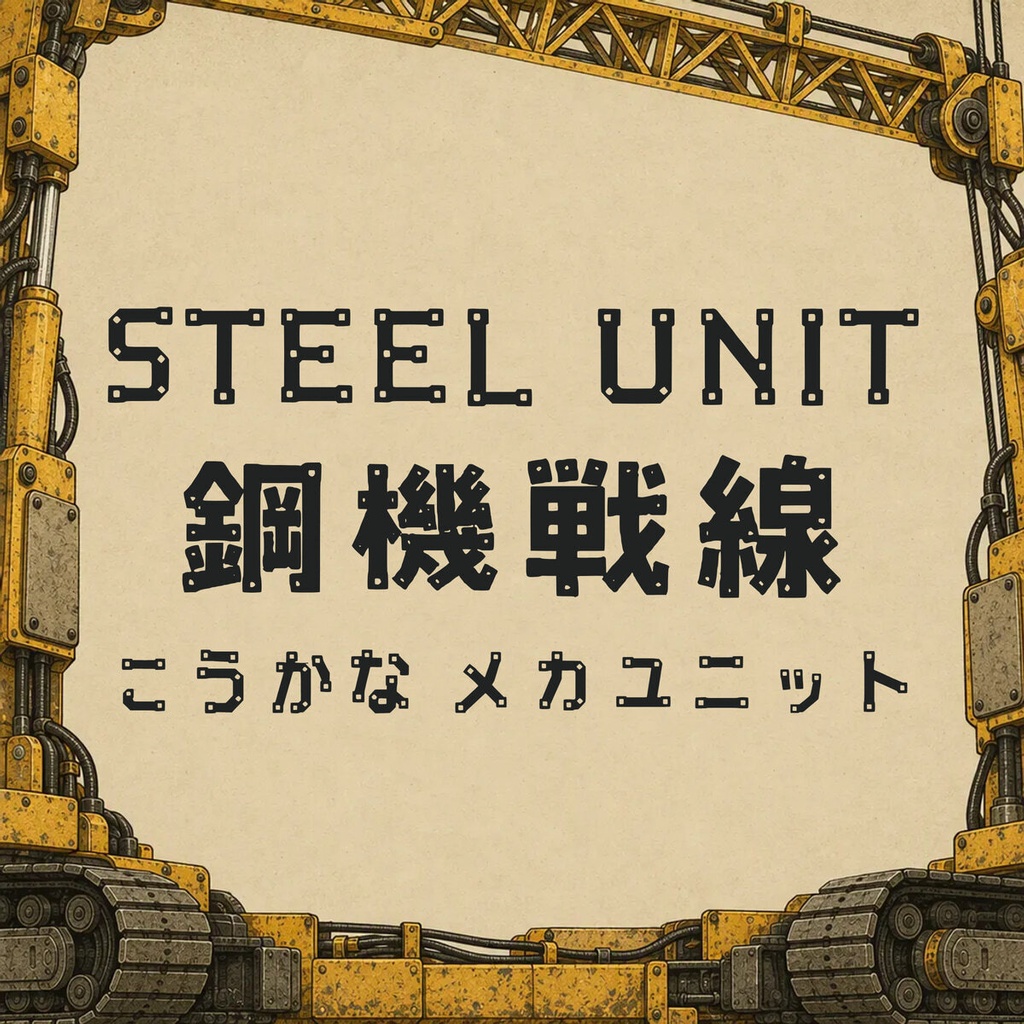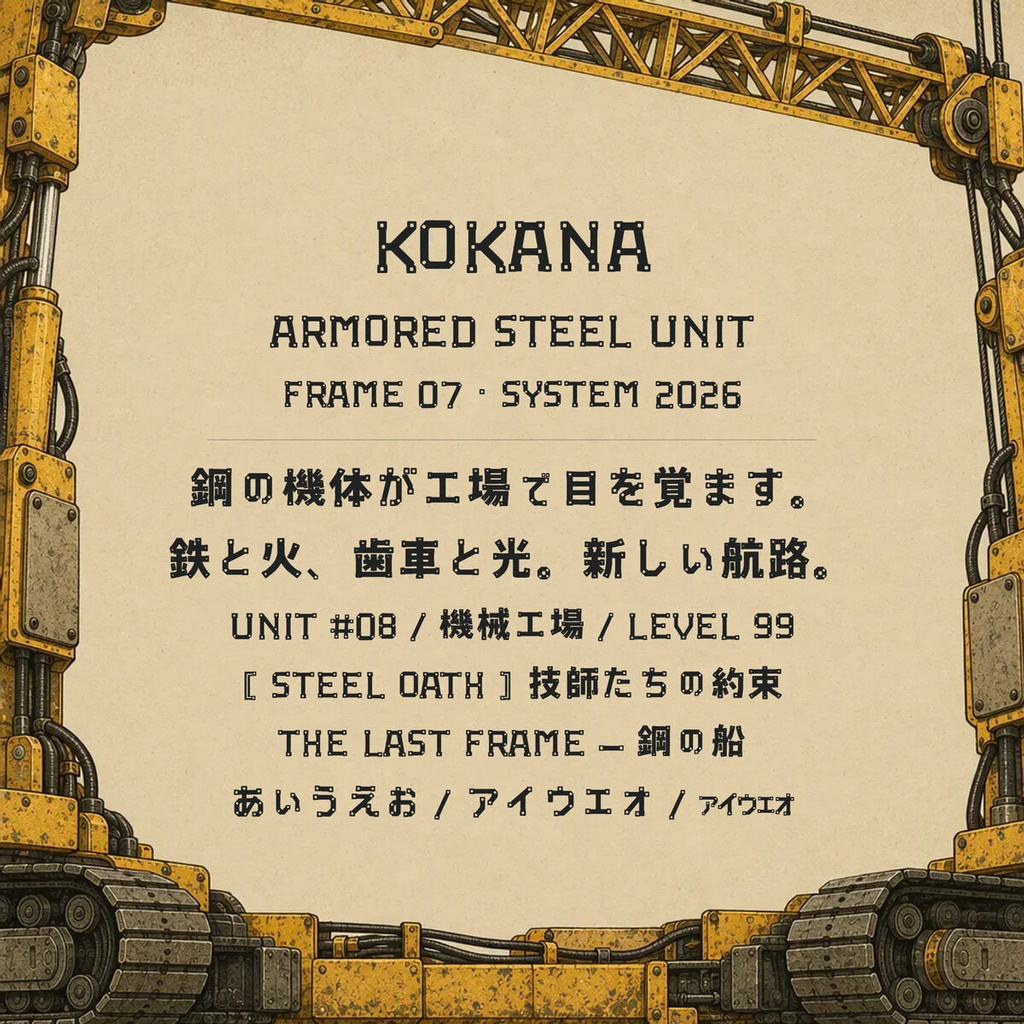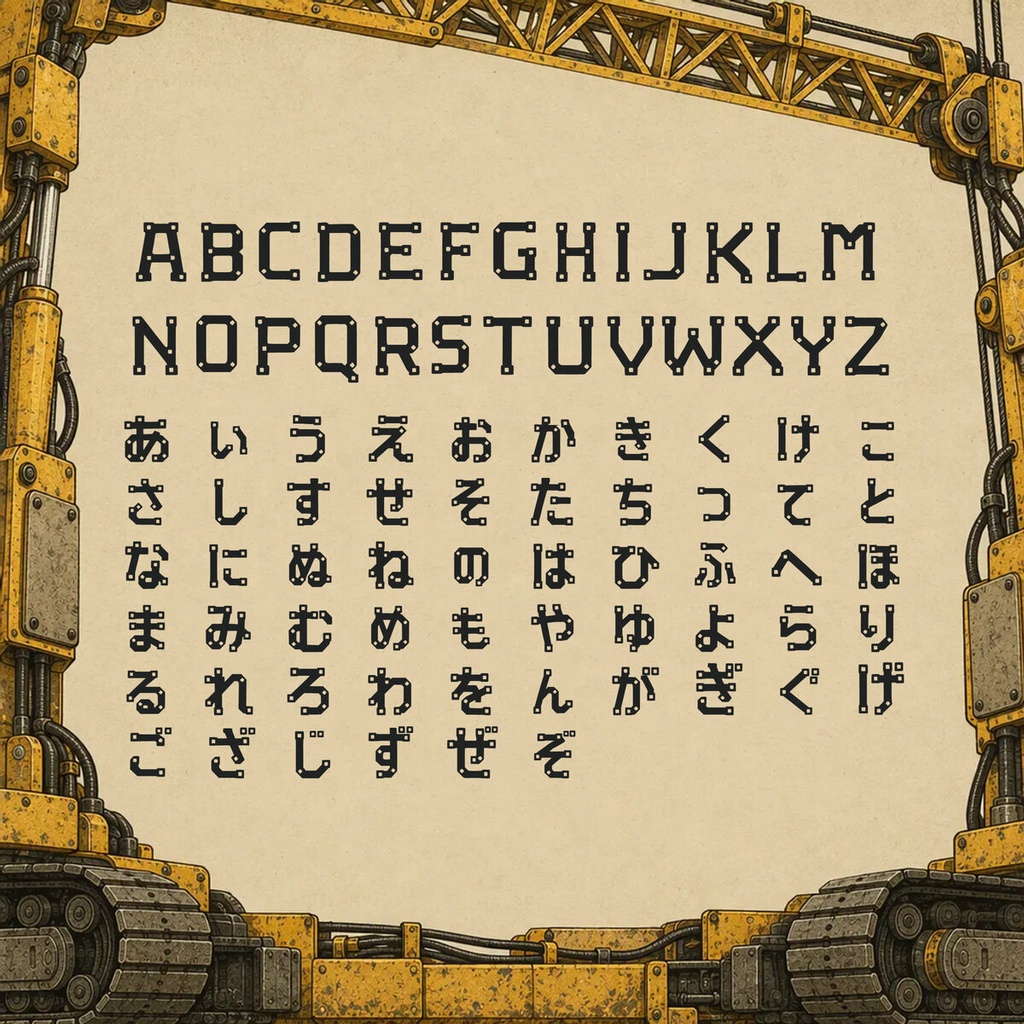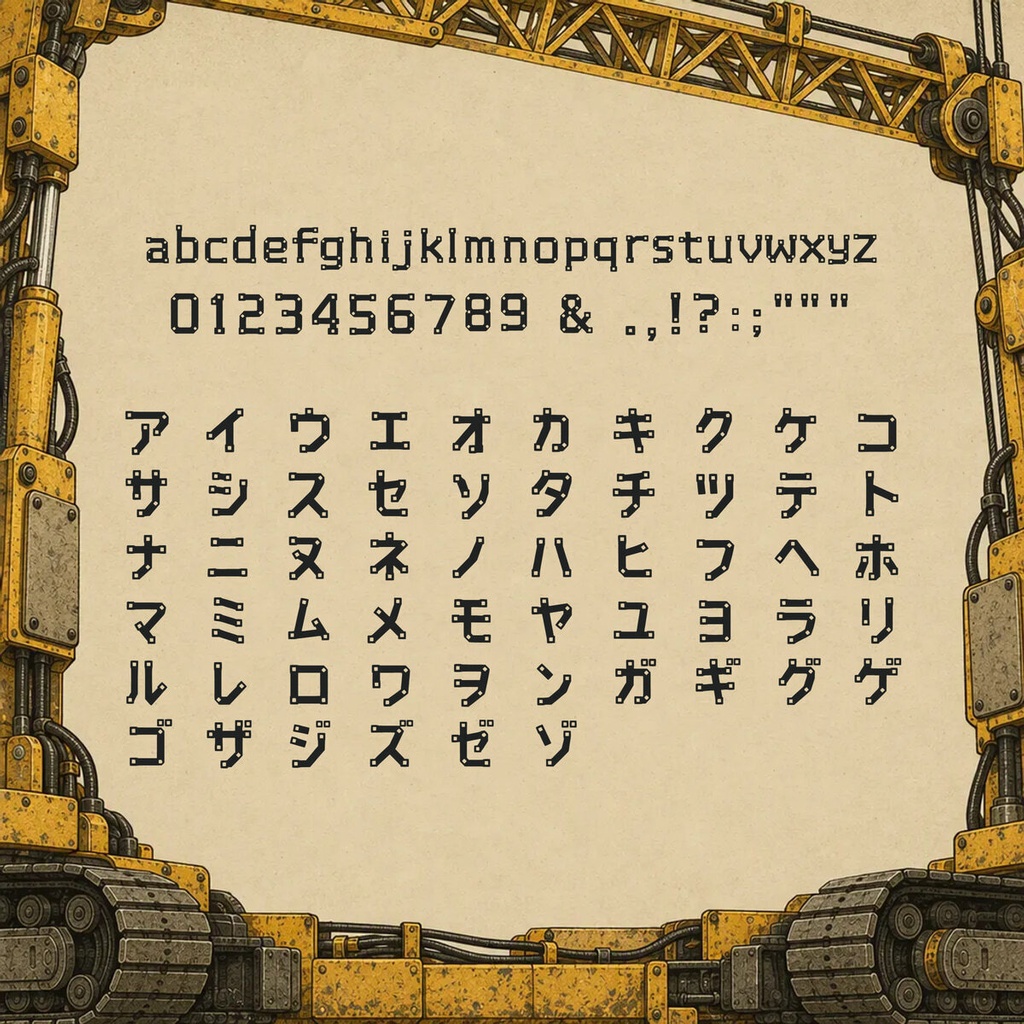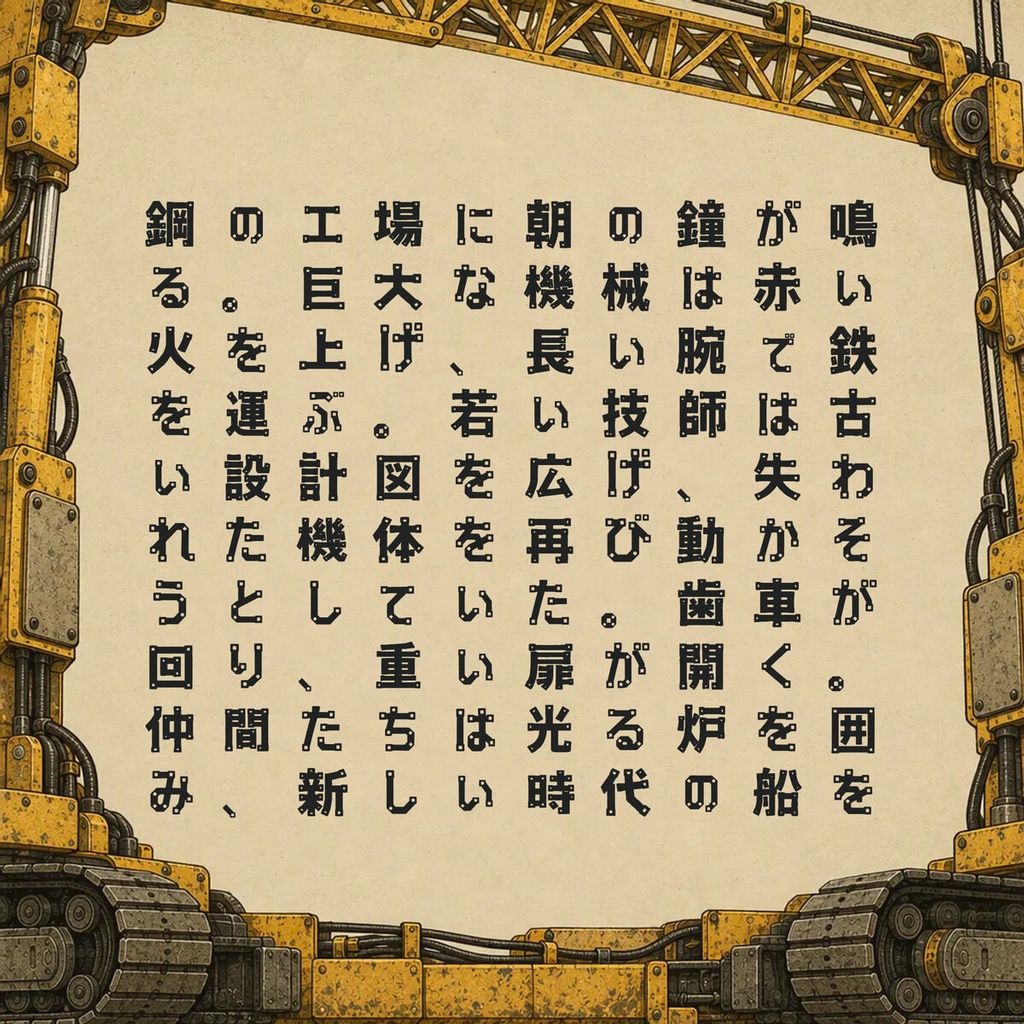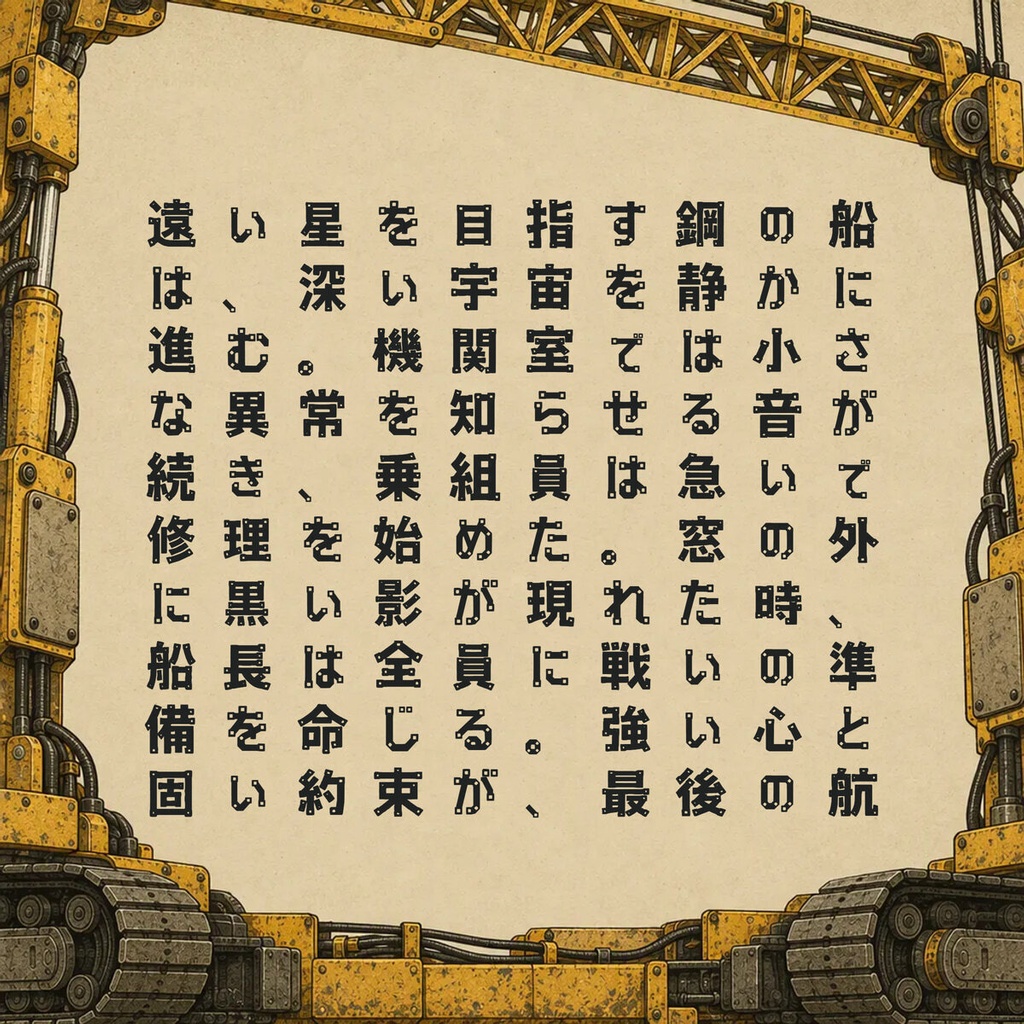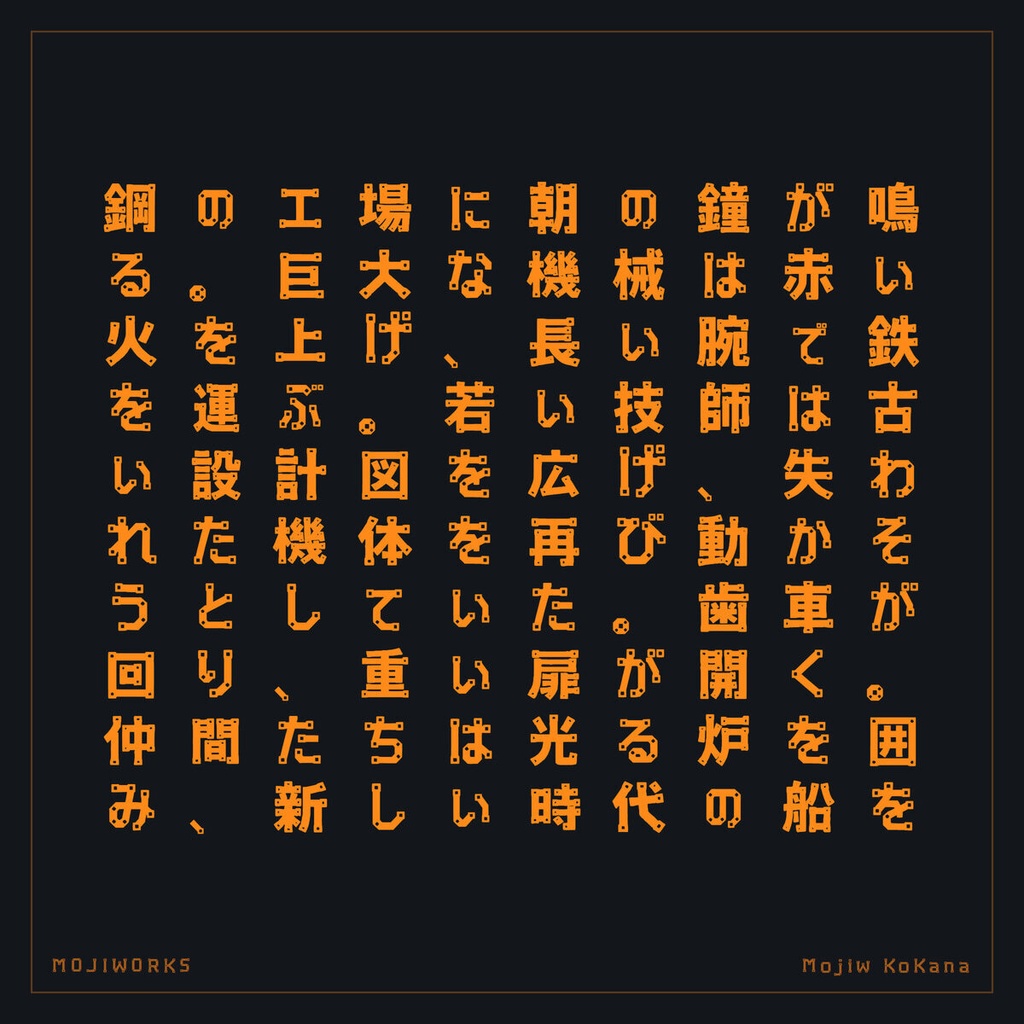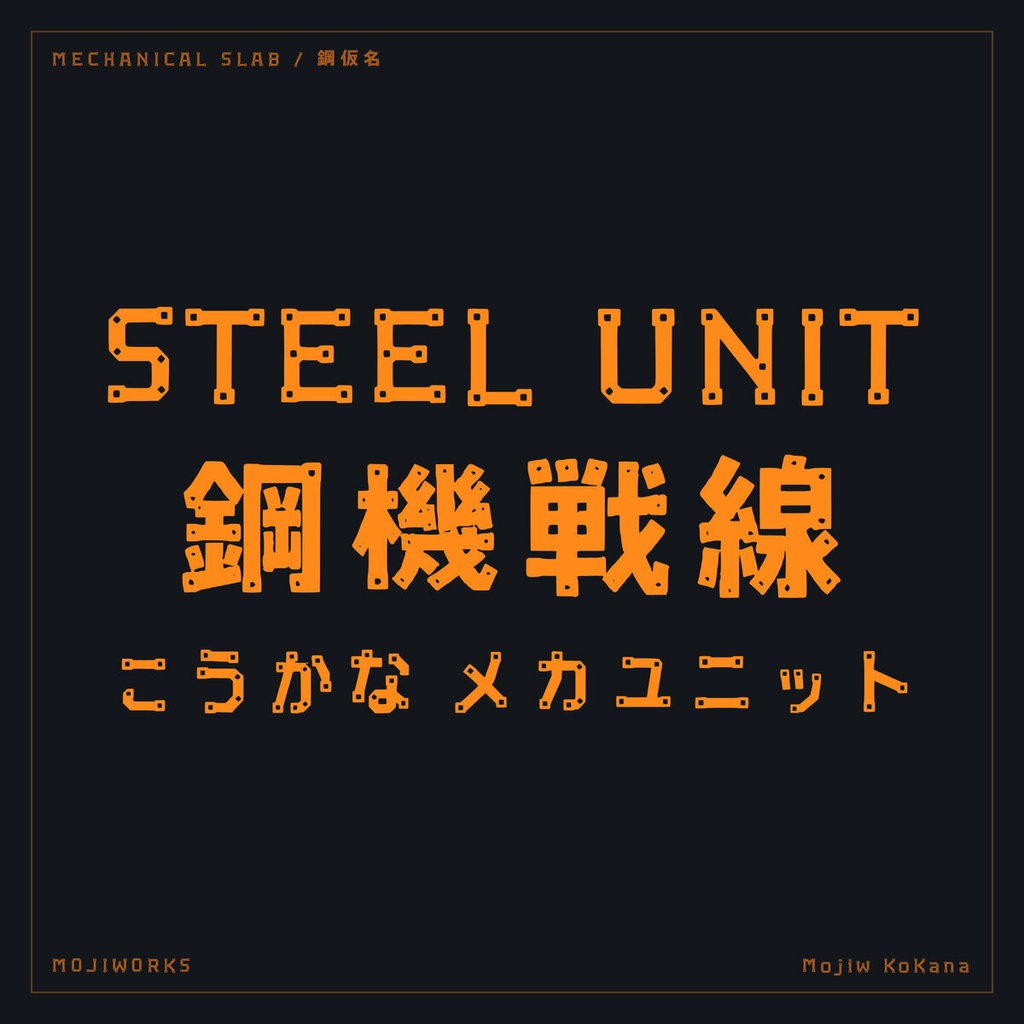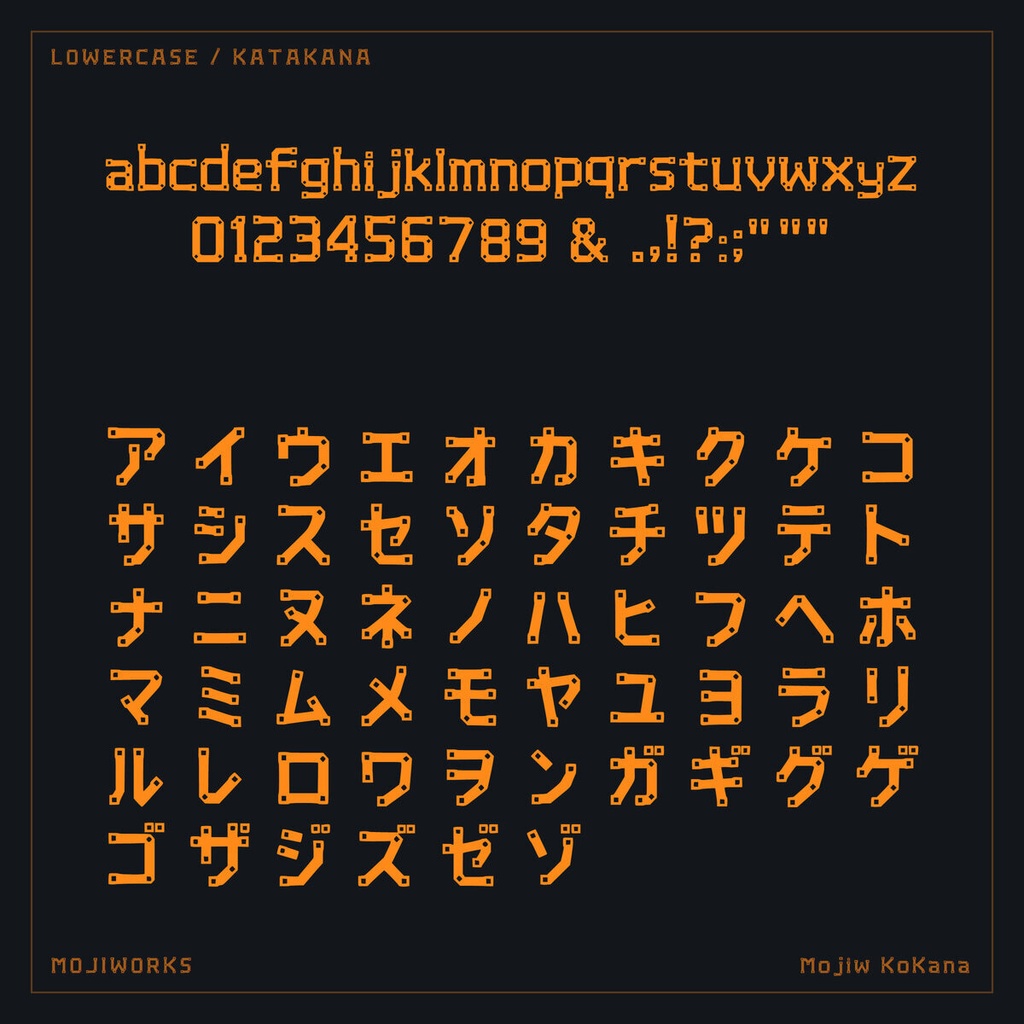
鋼仮名 KoKana【フォント】— メカ&インダストリアルスラブ|常用漢字2,136字
鋼の質感をまとった、メカ・インダストリアルスラブです。 A mechanical industrial slab engineered from riveted steel. 리벳을 박은 강철판처럼 설계한 메카·인더스트리얼 슬래브 서체입니다. 【用途 / Use / 용도】メカ / ロボット / SF / ゲームUI / 工業デザイン For mecha, robots, science fiction, game UI, and industrial design. 메카 / 로봇 / SF / 게임 UI / 인더스트리얼 디자인 ━━━━━━━━━━━━━━━━━━━━━━━━━━━ 【常用漢字フル版 / Full JA】 ━━━━━━━━━━━━━━━━━━━━━━━━━━━ 無料版の全文字と常用漢字2,136字を含む、全2,498文字を収録しています。 Includes 2,498 characters total: Latin, kana, symbols, and the complete set of 2,136 Joyo kanji. 常用漢字フル版 / Full JA: 2,498文字 — ¥3,200 ━━━━━━━━━━━━━━━━━━━━━━━━━━━ 【無料版で試す / Try Free】 ━━━━━━━━━━━━━━━━━━━━━━━━━━━ 購入前に、ラテン文字・かな・記号362文字を収録した無料版をお試しいただけます。 Try the free 362-character Latin/kana edition before purchasing. Kanji are not included in the free edition. ▶ 無料版 / Free edition: https://mojiworks.booth.pm/items/8826752 ━━━━━━━━━━━━━━━━━━━━━━━━━━━ 【フォント仕様 / Specification】 ━━━━━━━━━━━━━━━━━━━━━━━━━━━ 形式 / Format : OpenType TrueType (.ttf) / Web (.woff2) 文字コード / Encoding : Unicode 動作環境 / Platform : Windows / macOS / Web browsers 収録字一覧 / Charset : 各ZIP内の CHARSET.txt 同梱ファイル / Bundled files: .ttf — デスクトップ用 / desktop .woff2 — Web 用 / web README.txt / README.jp.txt LICENSE.txt / LICENSE.jp.txt CHARSET.txt — 収録字一覧 / character list portfolio.pdf — モジワークス全書体ポートフォリオ (EN) portfolio.jp.pdf — モジワークス全書体ポートフォリオ (JP) 商品プレビュー画像 / product preview images ━━━━━━━━━━━━━━━━━━━━━━━━━━━ 【利用規約 / License Summary】 ━━━━━━━━━━━━━━━━━━━━━━━━━━━ ご購入・ダウンロードにより本規約に同意したものとみなします。著作権は Mojiworks に帰属します。 By downloading or purchasing this font you agree to these terms. © Mojiworks. The bundled LICENSE.txt / LICENSE.jp.txt is authoritative; this is a summary. ●使用条件 / Permitted use - 1ライセンス = 購入者本人。個人・商用利用OK。 One license is granted to a single user (the purchaser). Personal and commercial use is permitted. - 静的・ラスタライズ済み成果物(印刷物 / 動画 / グッズ / ロゴ / タイトル / ラスタライズUI)は常に許可。 Static, pre-rendered output (print, video, merchandise, logos, titles, rasterized UI text) is always permitted. - 同梱 .woff2 を購入者本人のサイトで CSS @font-face によりWebフォントとして使用可。 The bundled .woff2 may be served via CSS @font-face on a website owned or operated by the purchaser. ●条件付き利用 / Conditional use — game / app / software embedding - ゲーム・アプリ・ソフトへの組み込みは、エンドユーザーが生の .ttf / .woff2 を抽出できない形式に限り許可。 例: SDF / MSDF フォントアトラス、ビルド時ビットマップ化、暗号化・独自フォーマットへのパッキング、難読化コンテナ等。 Embedding in games, apps, or software is permitted only if the raw .ttf / .woff2 cannot be extracted by end users (e.g. SDF/MSDF font atlases, build-time bitmap atlases, encrypted or custom asset packing, obfuscated containers). - 生の .ttf / .woff2 をビルドにそのまま同梱する用途は標準ライセンス対象外です。別途「ランタイム組み込みライセンス」をご相談ください。 Shipping the raw .ttf / .woff2 inside a build is NOT covered by the standard license — please contact us for a separate runtime-embedding license. ●利用規模 / Scale limit - 標準ライセンスは 1製品 / 1サイト あたり 年間およそ 100,000 インストール/ダウンロード/ユニークビジターまでをカバーします。 The standard license covers usage up to approximately 100,000 installs, downloads, or unique visitors per year, per product or site. - これを超える規模、または従業員 50 名超の組織(タイトルのパブリッシャー含む)でのご利用は「拡張ライセンス」をご相談ください。 Beyond this scale, or for organizations with more than 50 employees (including the publisher of the title using the font), please contact us for an extended license. ●禁止事項 / Prohibited - フォントファイル本体の再配布・譲渡・販売・貸与・サブライセンス。 Redistribution, resale, lending, or sub-licensing of the font file itself. - 生 .ttf / .otf の公開Webサーバー / CDN / ファイル共有サービスへのアップロード。 Uploading the raw .ttf / .otf to public web servers, CDNs, or file-sharing services. - 他者運営サイトからの .woff2 のホットリンク。 Hot-linking the supplied .woff2 from a site not owned by the purchaser. - フォーマット変換(独自Webフォント化を含む)、グリフデータの抽出、派生・類似フォントの制作・配布。 Format conversion (including building your own webfont), glyph extraction, or creating / distributing derivative or look-alike fonts. - 生成AIの学習、または画像・テキスト生成のスタイル参照としての使用。 Use for training generative-AI models or as a style reference for AI generation. - 本フォント自体の主たる商標としての登録(フォントで作った制作物の商標化は可)。 Trademark registration of the font itself as a primary mark (trademark of works made with the font is allowed). - 公序良俗に反する用途(誹謗中傷・犯罪助長・差別等)。 Use violating public order or morals (defamation, incitement to crime, discrimination, etc.). 詳細は同梱の LICENSE.txt / LICENSE.jp.txt をご確認ください。 For the full license, see the bundled LICENSE.txt / LICENSE.jp.txt. ━━━━━━━━━━━━━━━━━━━━━━━━━━━ 【カスタムフォント制作 / Custom Font Service】 ━━━━━━━━━━━━━━━━━━━━━━━━━━━ あなたのプロジェクトの世界観・雰囲気に合わせた、完全オーダーメイドのフォント制作を承ります。 ゲーム / アニメ / ブランド / VTuber / 同人作品のロゴ・タイトル用書体、独自スタイルのディスプレイ書体、収録字の拡張など、お気軽にご相談ください。 We craft fully custom fonts tailored to your project's visual identity and requirements. Please contact us for original display faces, logo/title fonts, expanded character coverage, extended licenses, or runtime-embedding licenses. ▶ Mojiworks ショップ / Shop: https://mojiworks.booth.pm/